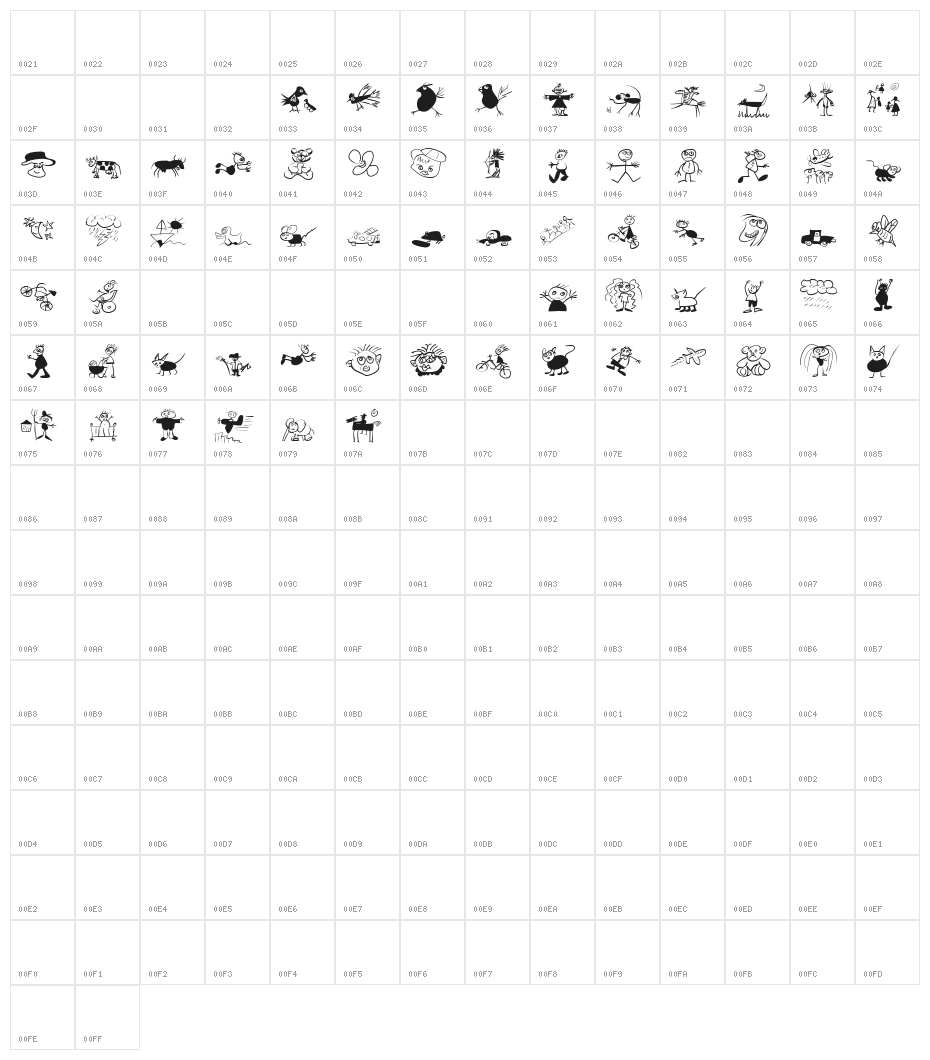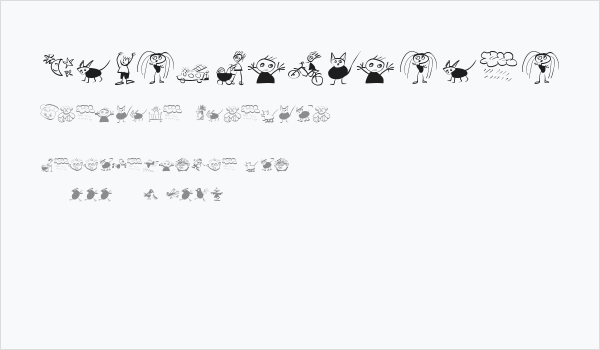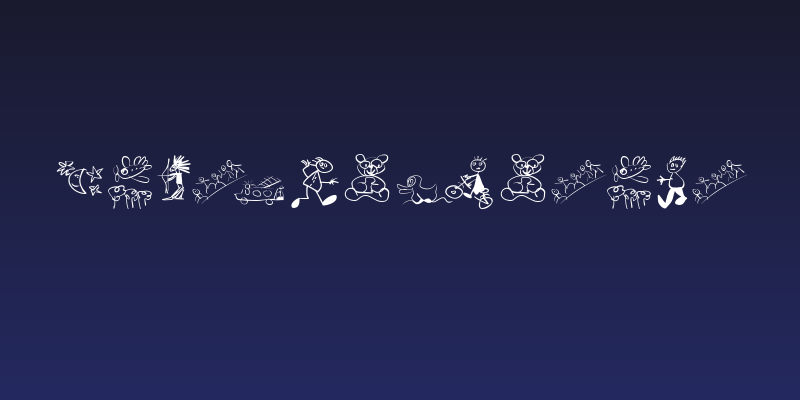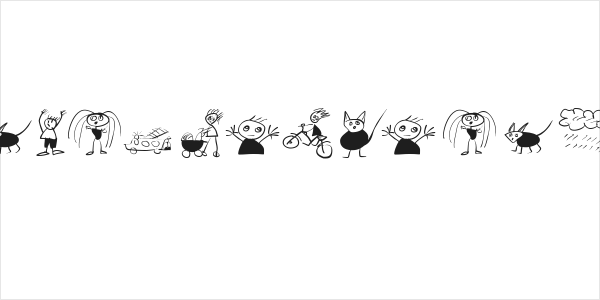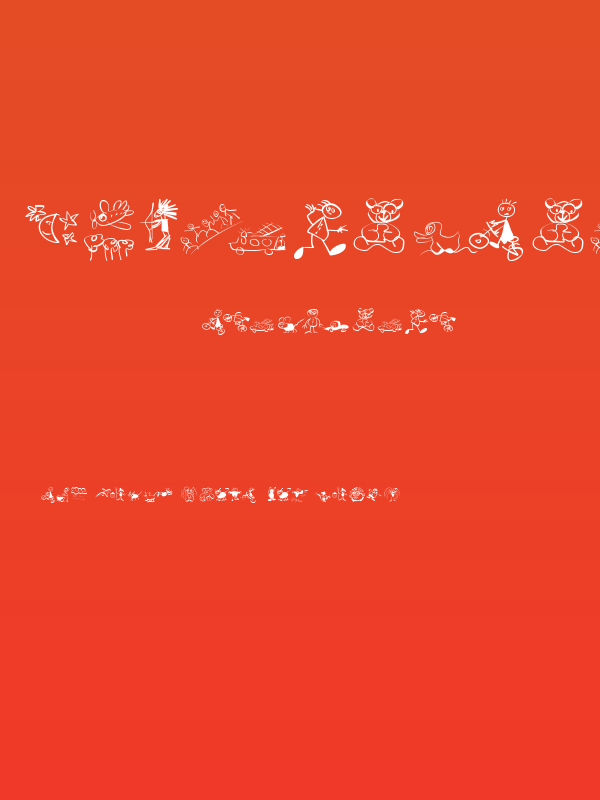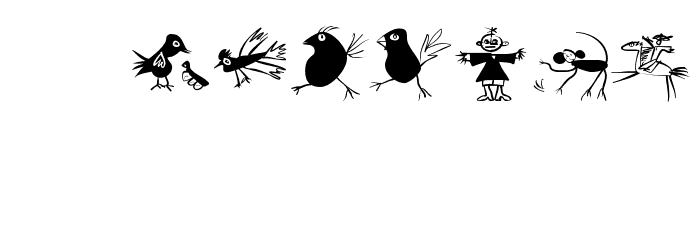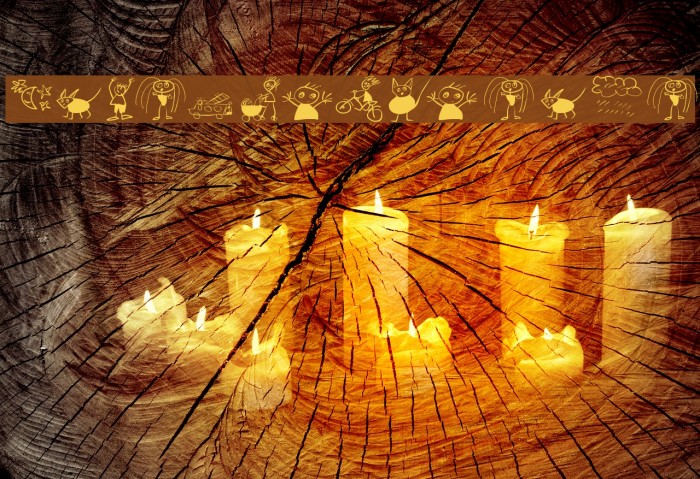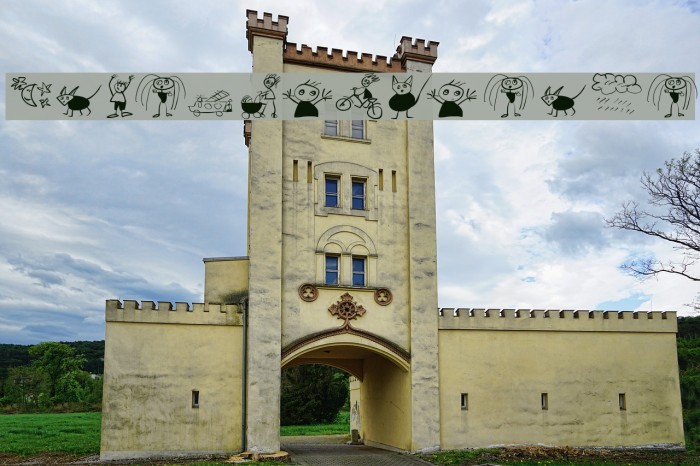
KidsPhantasies Font
| Stile generale | Playful, Childlike, Whimsical |
| Caso d'uso | Illustrative accents, decorative elements, thematic graphics. |
| Progetti proposti | Children's books, educational materials, party invitations, playful branding, classroom decorations. |